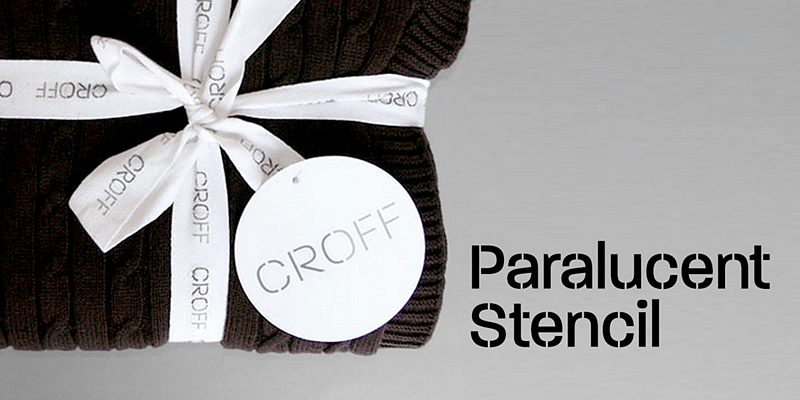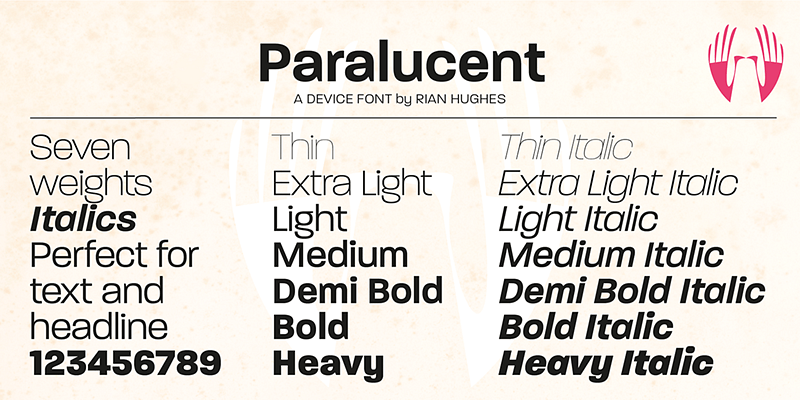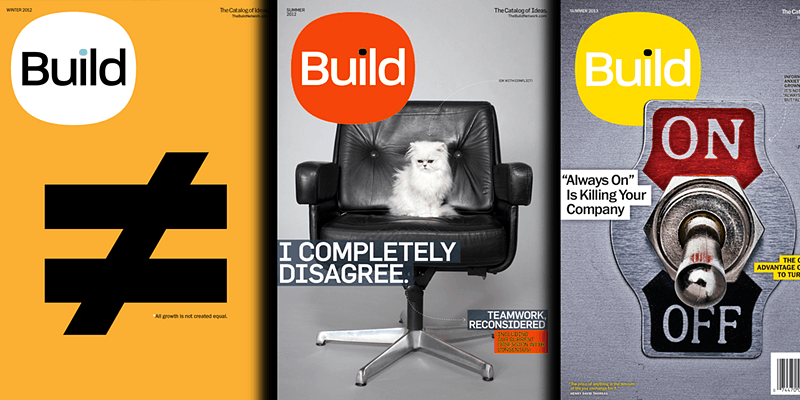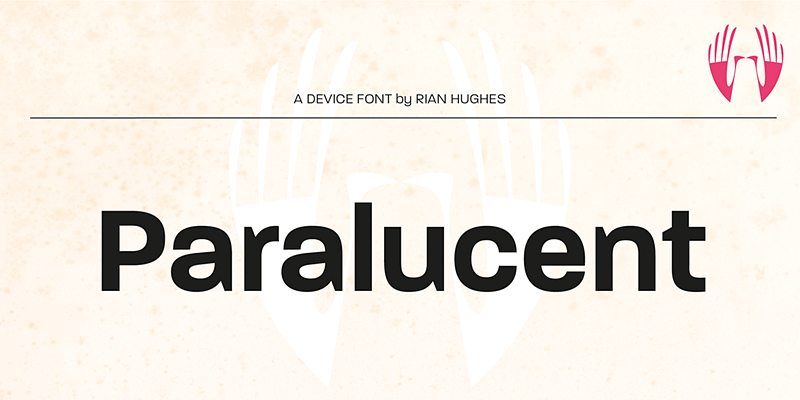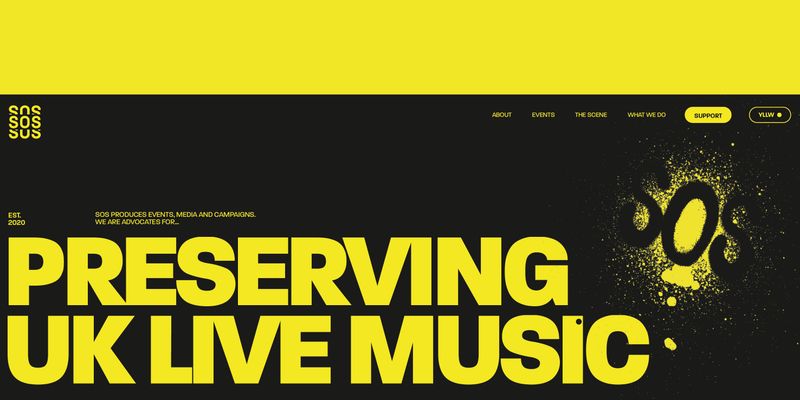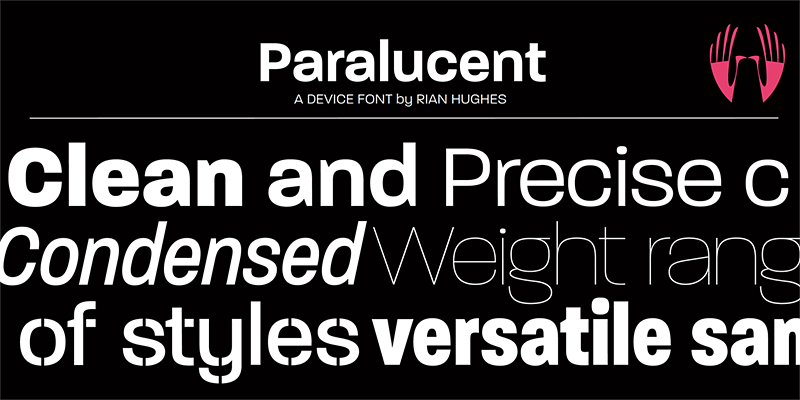
Una bestia de carga polivalente, esta gran familia es limpia, precisa y elegante a la vez que directa e indiscutible. Los grosores de texto están diseñados para tamaños pequeños.
Tipo, diseño e imagen del ilustrador y tipógrafo inglés Rian Hughes.